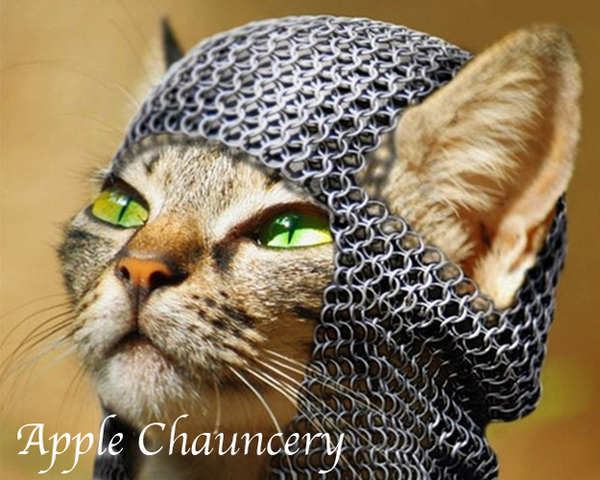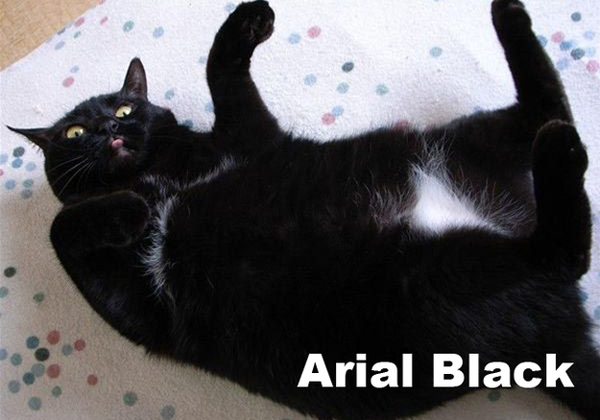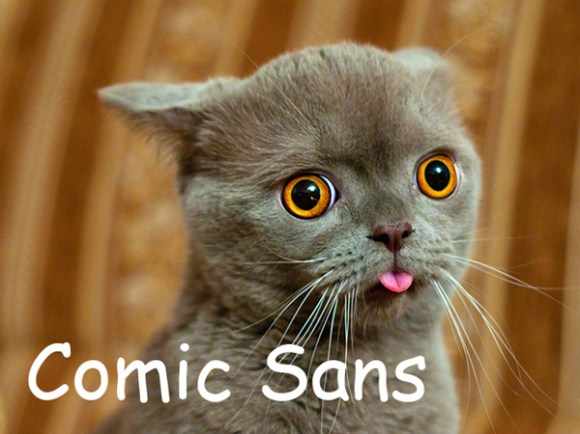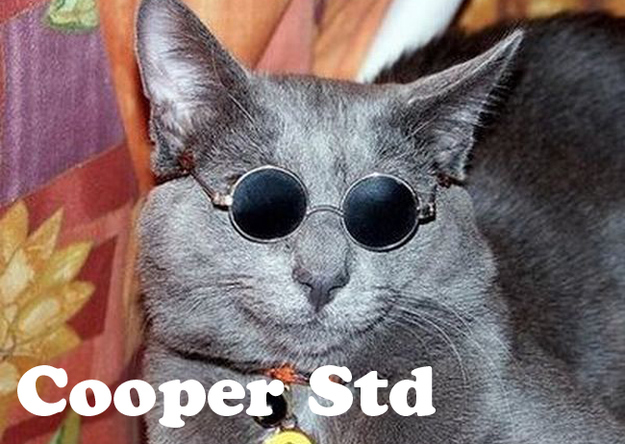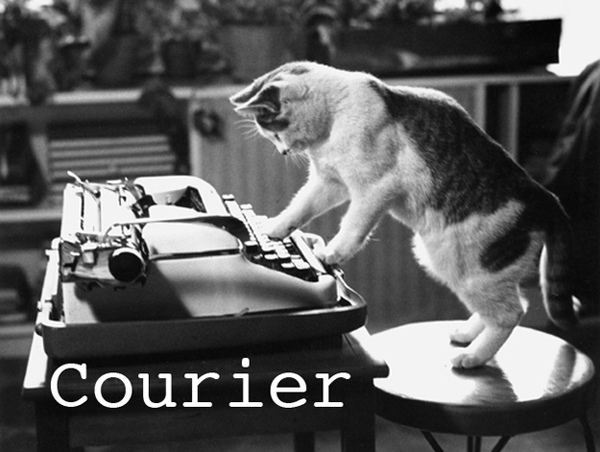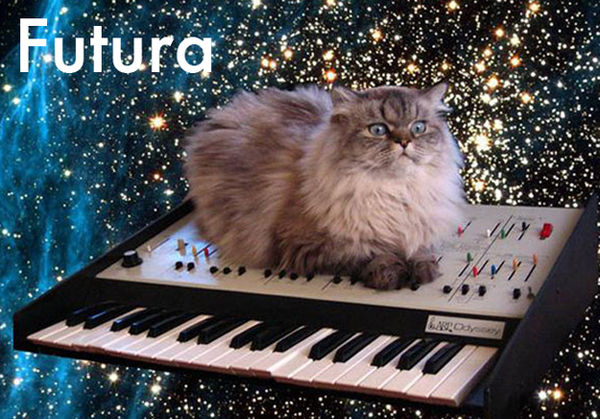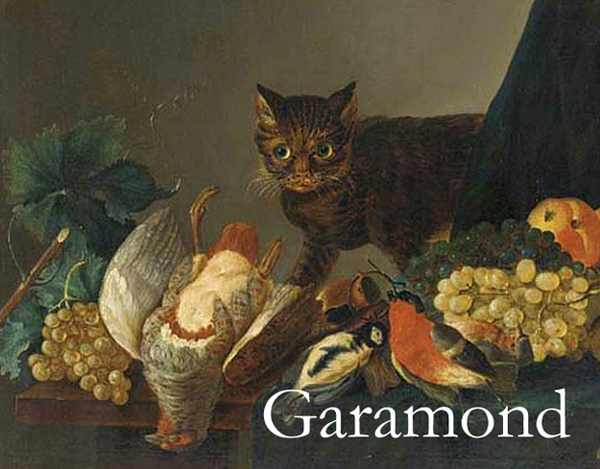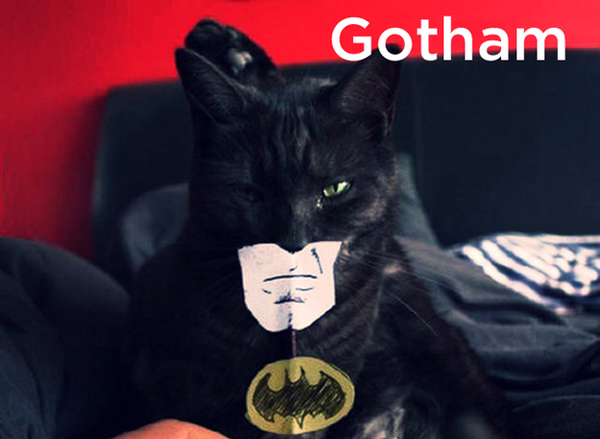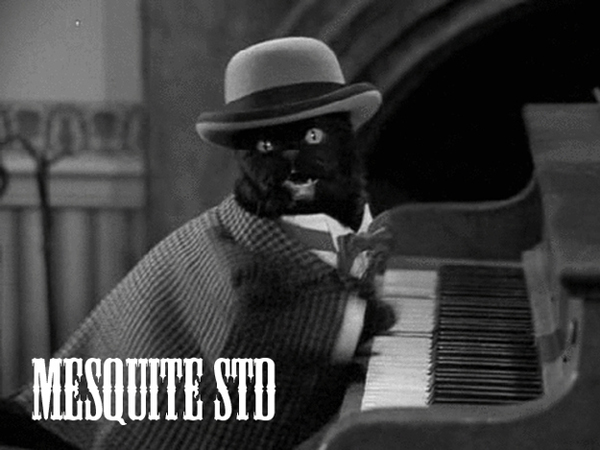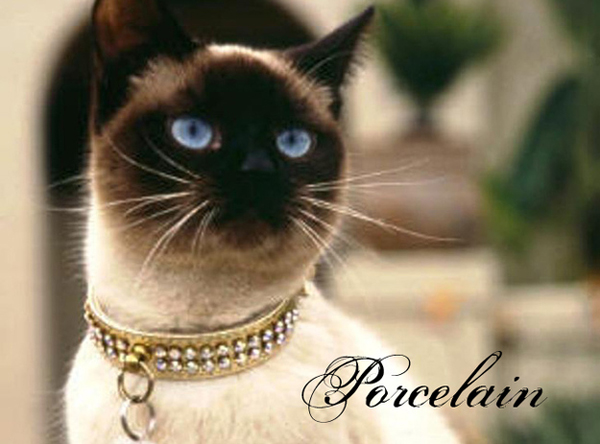
Si las tipografías fueran gatos
En BuzzFeed han conseguido juntar dos de mis pasiones, los gatetes (amor mortal de necesidad, dado mi horrorosa alergia) y la tipografía (querencia derivada de mi profesión y obsesión terrible que procuro sobrellevar lo mejor y más dignamente posible), en estas divertidas veinte imágenes en las que un minino hace las veces de representante de las más insignes familias tipográficas.
La Helvética es adorable y molona al mismo tiempo, como es lógico…